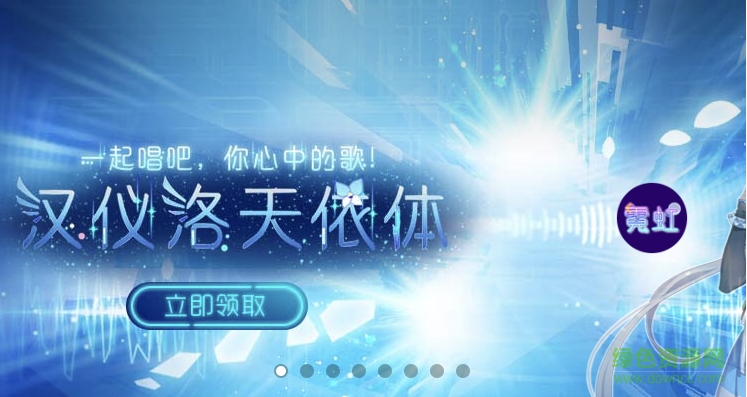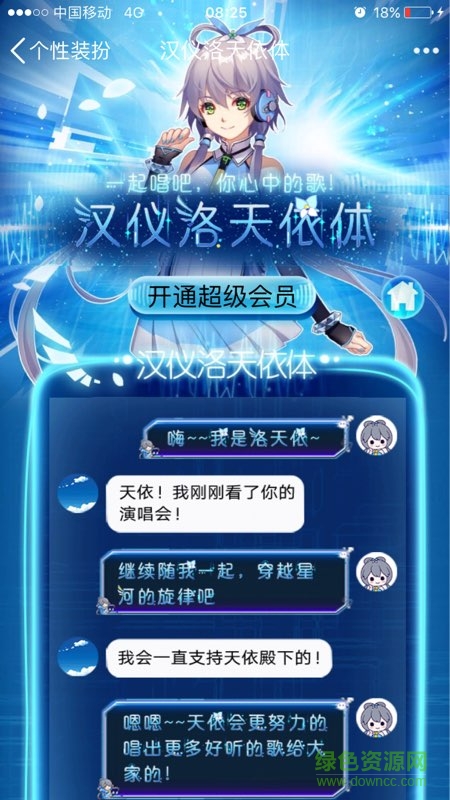
漢儀洛天依體是首款漢儀次元系列字體,該字體清晰脫俗,十分可愛,點(diǎn)綴圖案萌萌噠,喜歡洛天依的朋友們記得收藏下載哦,綠色資源網(wǎng)為您免費(fèi)提供!
該字體以動(dòng)漫洛天依角色為背景,字體筆畫盡顯其萌系特征,非常的呆萌可愛,整體效果十分時(shí)尚好看,感興趣的朋友歡迎免費(fèi)下載使用!